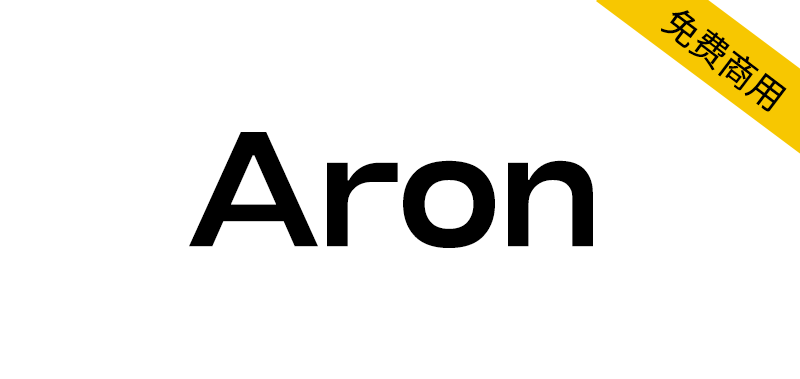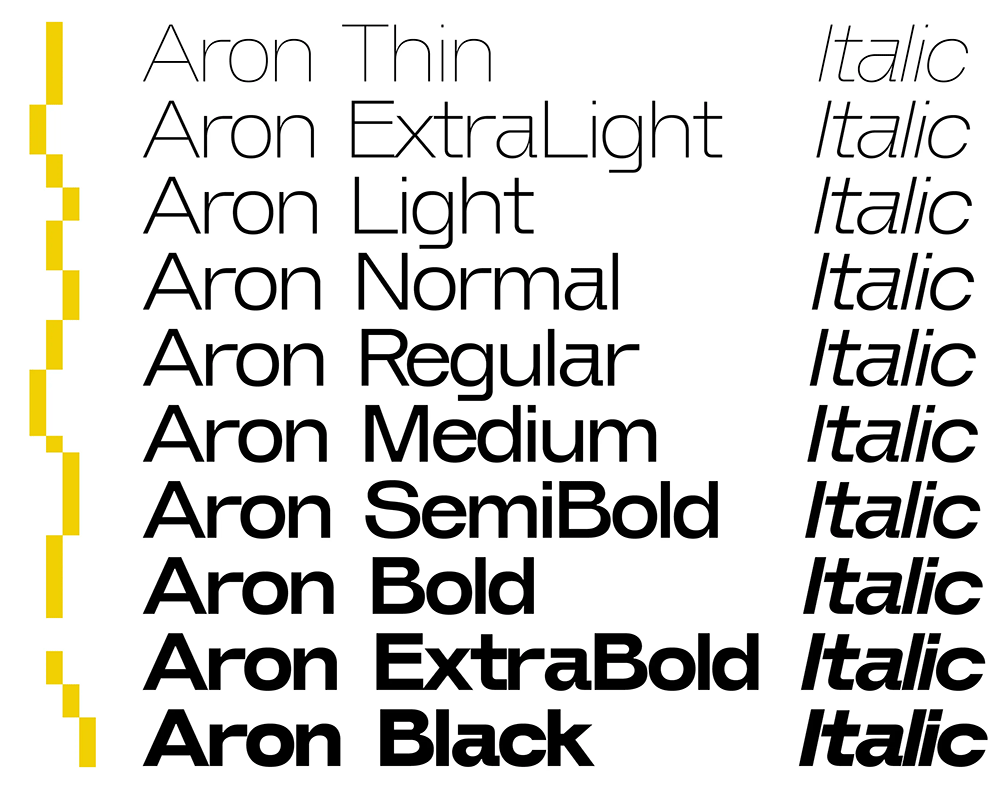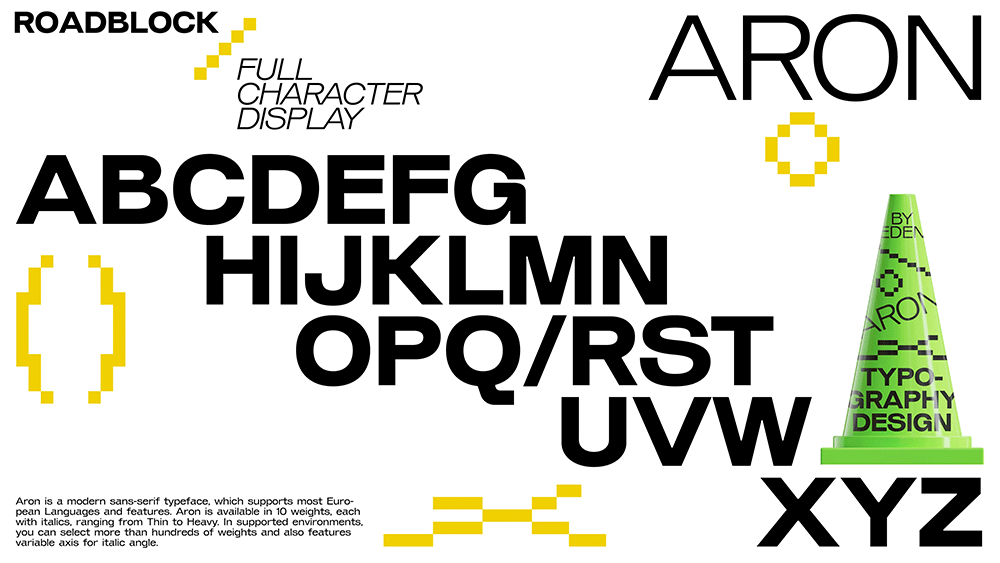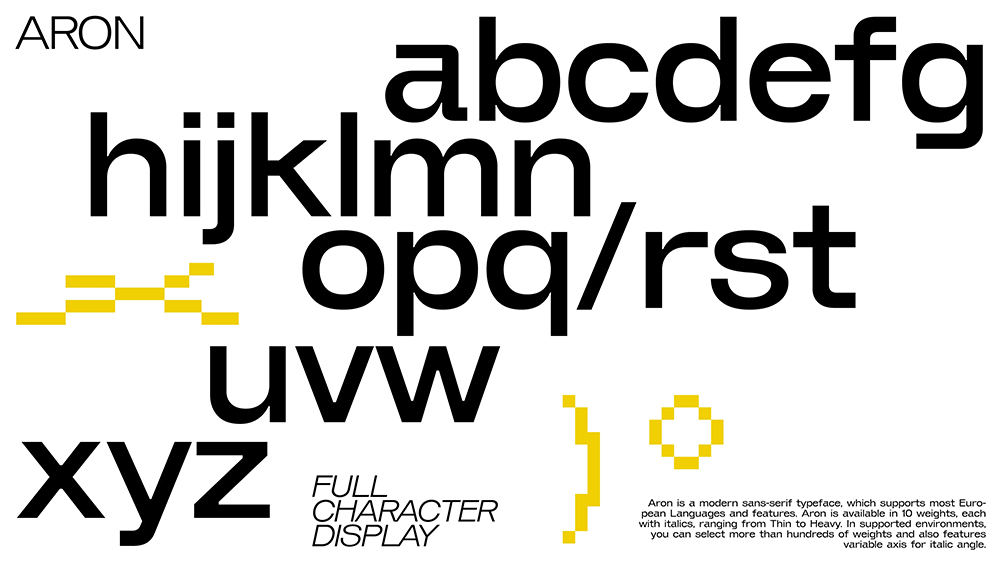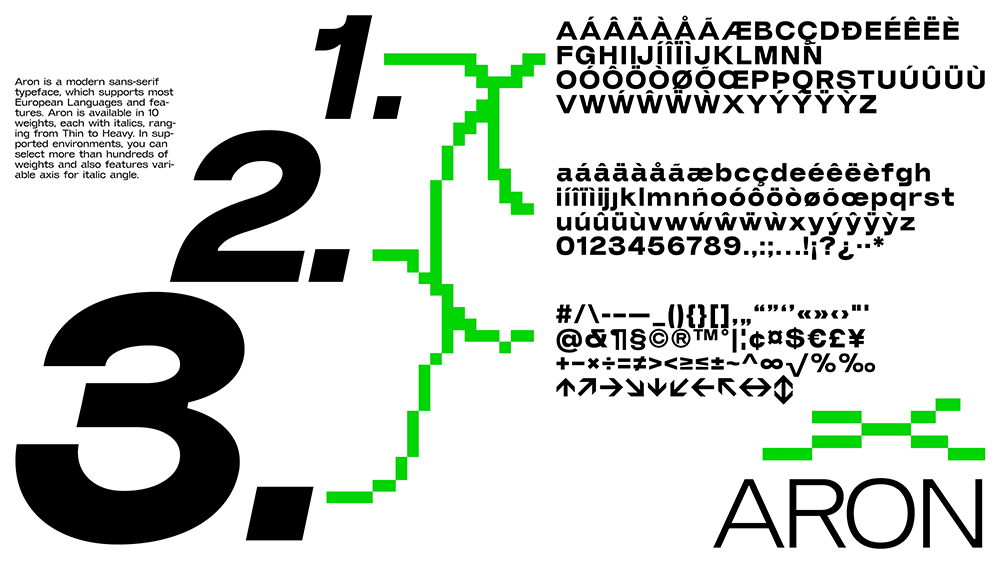
【Aron】带有意大利体的现代无衬线英文字体
Aron是一款现代无衬线字体,支持大多数欧洲语言和功能,Aron有10个字重可供选择,从特写到特粗,每个字重都带有意大利体。同时它带有可变版本,在应用支持的情况下,能在字重和倾斜角两个可变轴上自由调整。我们将对这款字体开放授权,用户可以自由地将其应用于各种设计场景中,希望你能喜欢。